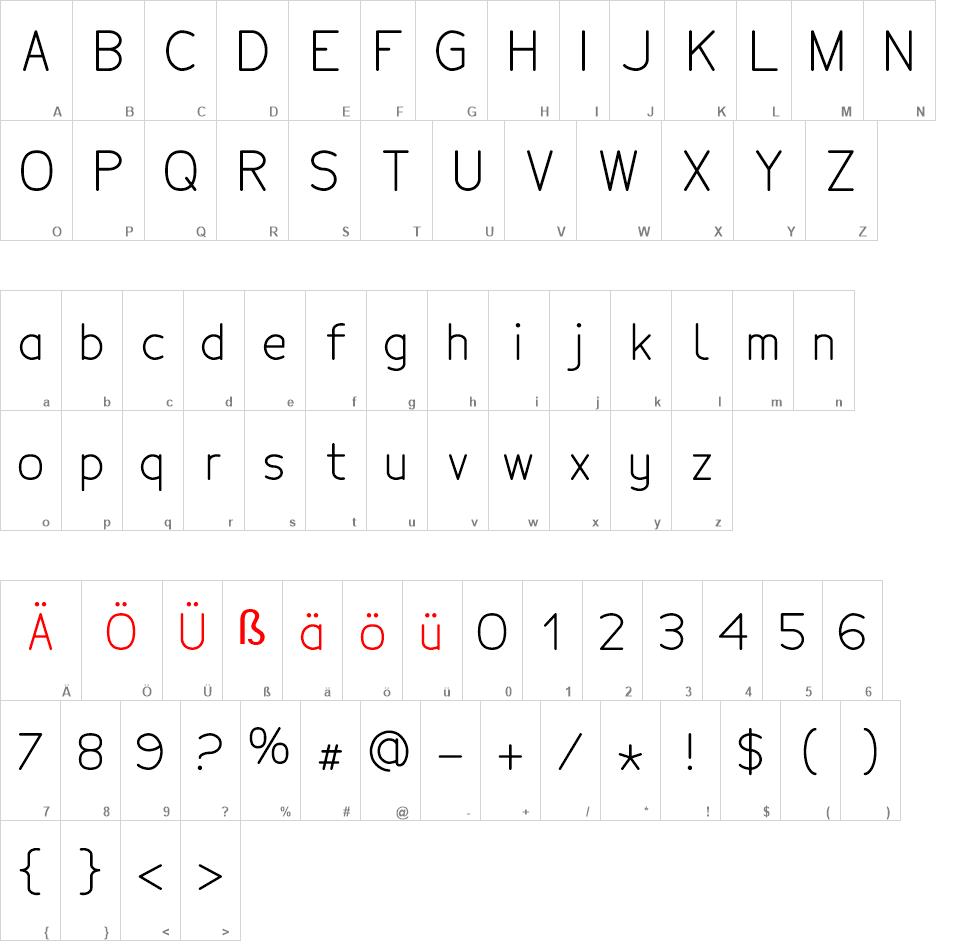
Tecnico Font Family
Die Schriftart "Tecnico" steht für die standardisierte Schrift, die in Architektur- und Ingenieurplänen verwendet wird und wurde gemäß den Angaben von IRAM 4503 erstellt.